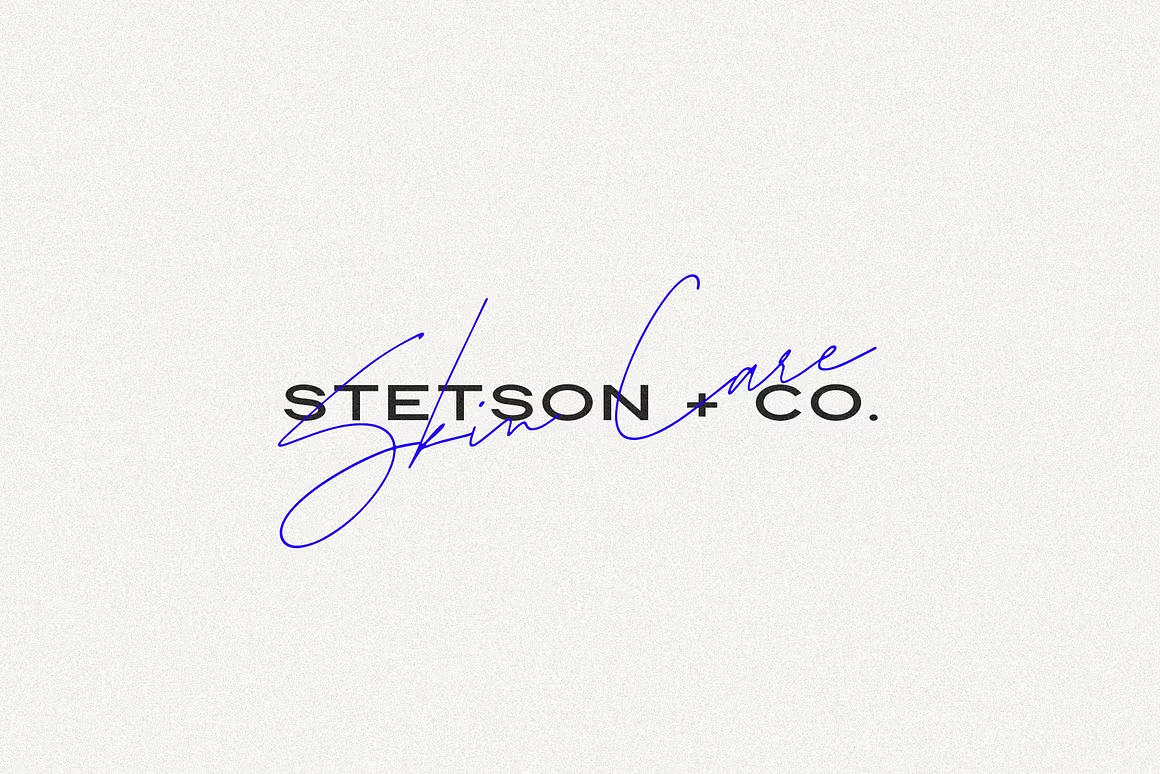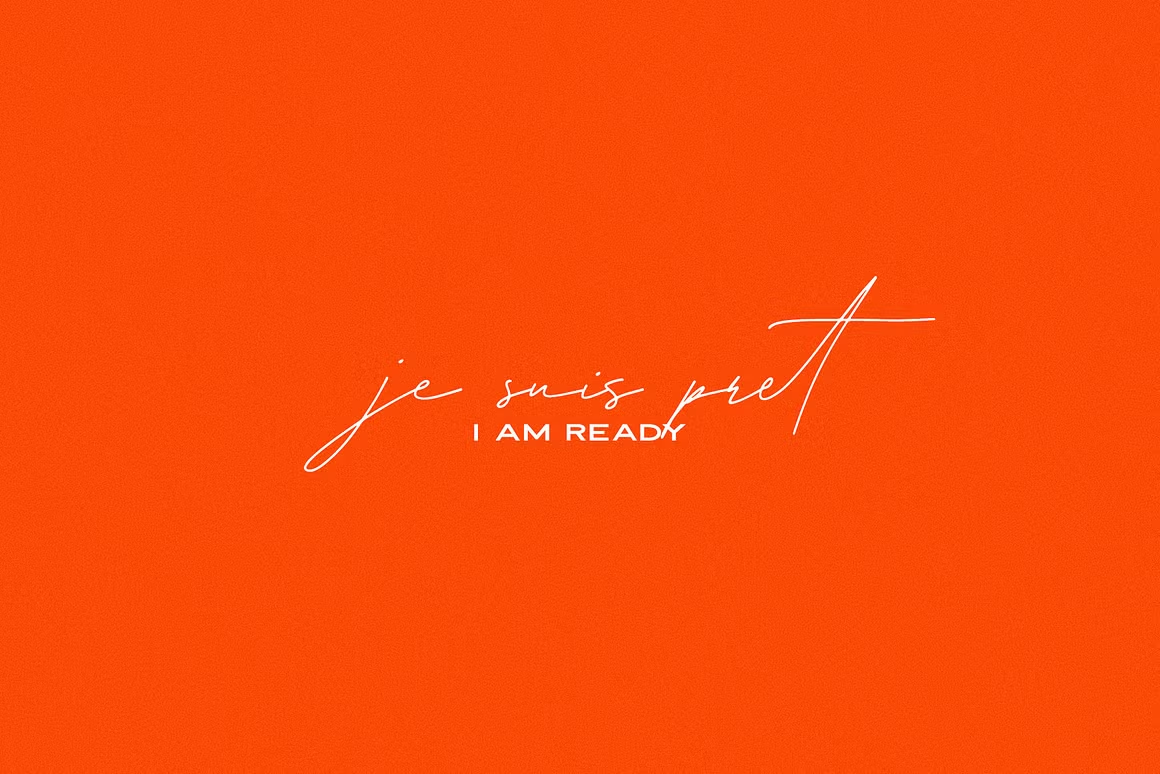
Modena Font
Description de Modena Font
Modena est un magnifique duo de polices de haute couture qui crée de superbes logos, affiches, invitations de mariage, articles de blog, réseaux sociaux et bien plus encore !
J’adore les utiliser avec des masques de calque dans Photoshop, il semble donc que le script parcourt les lignes du sans empattement. Le Sans est superbe avec un suivi réglé sur 220, qui tombe généralement à 0 !
Modena Script comprend plus de 50 ligatures pour que tout ait l’air fait à la main et des alternances pour chaque lettre.
Lettres majuscules et minuscules avec suppléants
Chiffres + Ponctuation
Prise en charge dans une langue autre que l’anglais
Plus de 50 ligatures